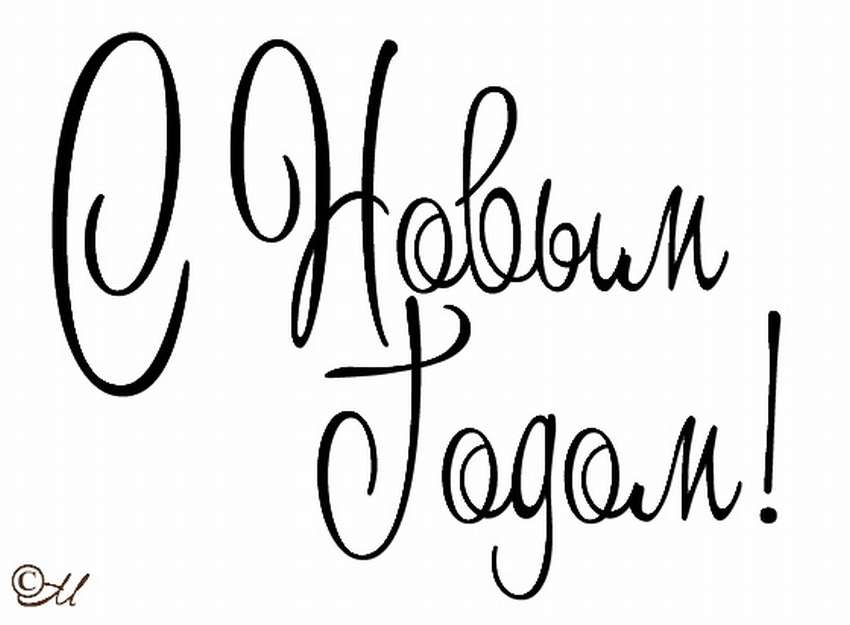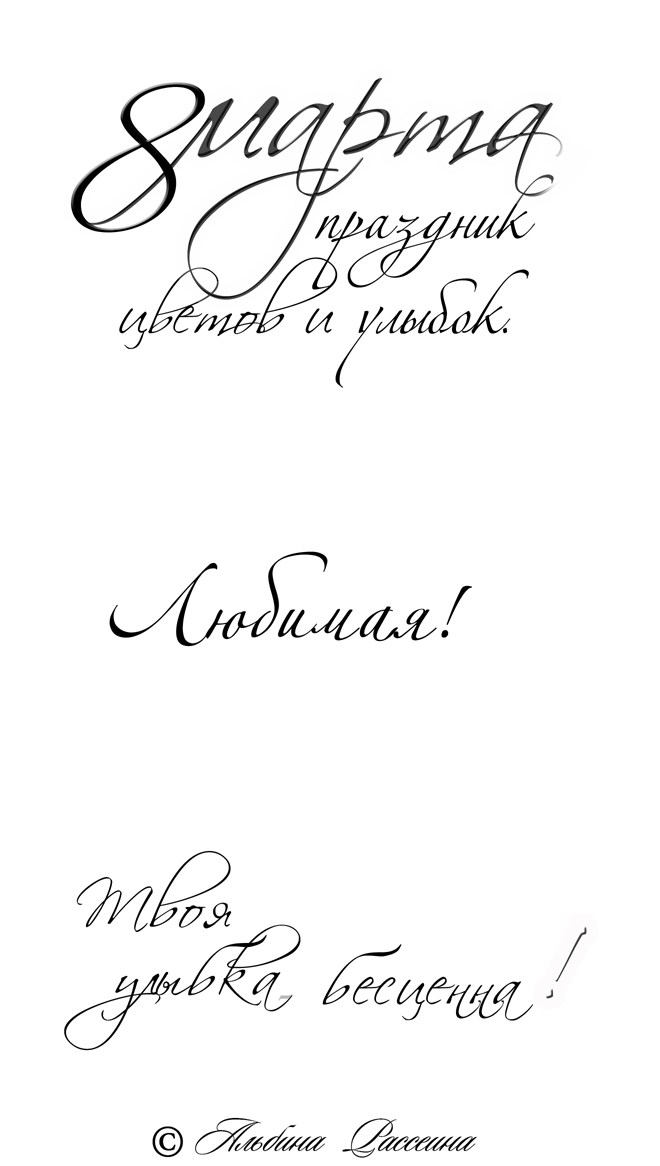
…Братушка делал корпоративную открытку ко Дню Победы.Серьезному строительному холдингу хотелось поздравить своих пенсионеров — фронтовиков, а депутатствующему директору компании – фронтовиков своего избирательного участка. Но не просто поздравить, а с душой и в фирменном стиле.
Рекламное агентство взялось выполнить заказ. А что – рядовая работенка.
С оборотом открытки проблем не возникло – логотип компании и место для поздравительного текста.
С лицом оказалось сложнее.
Поставить классического поднимающегося в атаку политрука? Избито.
Флаг над рейхстагом? Во всех газетах будет на первой полосе.
Сфотографировать местный Вечный огонь? Официозно.
Использовать старые плакаты? Старые открытки? «Родина-мать» и «Алеша». Не то. Все – не то. Эпоха сменилась. Чувства сменились…
Подумав, Братушка велел дизайнеру найти фотографию — алые маки по зеленому лугу, и на этом фоне написать четыре слова: «С ДНЕМ ВЕЛИКОЙ ПОБЕДЫ!».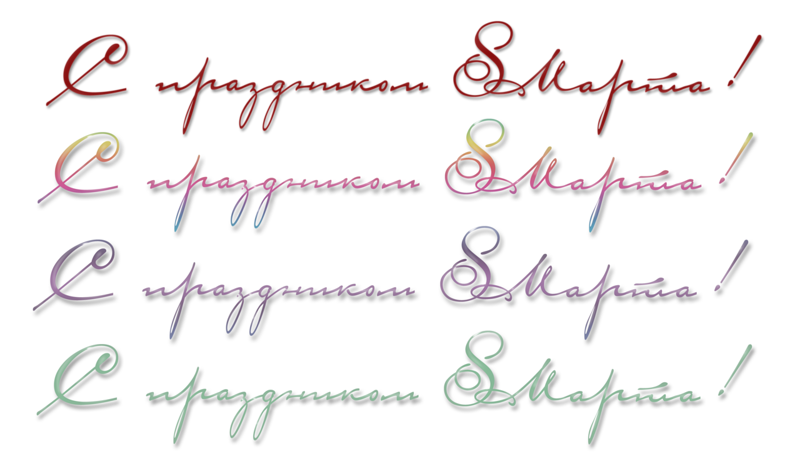
Снимок нашелся. Слоган поставили. Не играет!
Снимок правильный — щемящий до слез. А шрифт – бездушный. Чужой шрифт. Не из ТОЙ эпохи.
Сели выискивать среди компьютерных шрифтов такой, который бы визуально в пятидесятые отсылал. А не выходит. Получаются или революционные годы. Или излет восьмидесятых. Или вообще что-то эмоционально невнятное.
Сидят Братушка с дизайнером, перебирают по очереди шрифт за шрифтом. И после очередного клика видят картинку.
Новая зеленая жизнь, поднимающаяся на залитом маками, словно кровью, среднерусском поле. И под этим всем — написанное суровой готической (а может и вовсе – тевтонской) вязью — «С ДНЕМ ВЕЛИКОЙ ПОБЕДЫ!».
И тут Братушка словно в другую реальность провалился. Говорит: «Смотрю в монитор и вижу совсем другой парад на Красной площади. Другие знамена. Другие порядки. Слышу и дизайнер моя нервически хихикает и шепчет:
— Бли-ин, а если бы вот так вышло…»
…Запотыку со шрифтом решили по-старинке. Дизайнер взяла плакатное перо, и с трех попыток написала поздравление тушью.
Сосканировали, вставили. И да – стилистически наконец попали в конец сороковых — начало пятидесятых.
Заказчик был доволен. Фронтовики, говорят, даже плакали.
А Братушка тот случайный «тевтонский» вариант открытки уничтожил. Даже в качестве дизайнерской шутки никому показать не решился. Даже мне. Только на словах и поведал, что такое «страшно смешно» в историческом контексте.
Как приятно получать поздравления! Как приятно поздравлять!
Поздравительная открытка ручной работы – один из самых простых и в то же время изящных способов сделать приятно любимому, уважаемому, дорогому человеку.
В старину открытки появились как открытый вид письма — карточки с открытым текстом. После их стали украшать различными изображениями. Первая иллюстрированная открытка была напечатана во Франции.
Сейчас открытка, сделанная специально для человека, для мероприятия (пригласительная открытка на свадьбу) стала очень популярной, и получить её в подарок — всегда приятно!
Я считаю, что лучшая открытка – это открытка ручной работы, сделанная индивидуально для конкретного человека, учитывая его чувства, характер и интересы, потому, что самый дорогой подарок – это внимание и уважение.
В этом случае – авторская рукописная открытка – подходит более всего. Нарисованная профессиональным художником иллюстрация, с текстом, написанным от руки каллиграфическим почерком (шрифтом) придаёт простому подарку безупречную элегантность и изысканность. Такой подарок без сомнения дарить и получать очень приятно!
Именно каллиграфический шрифт передаст всю восторженность события, всю радость приближающегося праздника. Самим выбором шрифта, написанием букв уже можно угадать характер самого человека. Уже буквами — раскрыть образ нежной девушки, чопорной дамы, веселого юноши.
Красиво сочетать каллиграфические буквы с изображением, выстроить композицию меня учила моя лучшая преподавательница — Елена Анатольевна Дербилова. Эта потрясающая женщина вместила в себя и музыку (играла на скрипке), и танец (балет), и изобразительное искусство. Но по её мнению — рукописный шрифт вбирает все эти три понятия — он создаёт новую музыку, буквы — застывают танце…
Каждый раз, когда меня просят сделать открытку — я подхожу ответственно.
Данные примеры двух открыток — адресованы девушке. Поэтому они нежны и поэтичны, как сама получательница, а рукописным шрифтом я хотела передать её непоседливый характер.
По-моему – получилось.
20 лучших контурных шрифтов cкачать бесплатно Ⓐ Shriftkrasivo.ru
В итоге мы получаем текст, который выглядит волнистым.
Перейдите в Объект> Разобрать оформление. Это превратит наш текст в точки и линии, с которыми будет легче работать в следующих шагах.
Шаг 4. Измените цвета обводки и заливки
Мне нравится идея сильного контраста красных и черных теней, как на открытке Massachusetts , поэтому давайте перенесем эту концепцию в наш дизайн.Все, что нам нужно сделать, это изменить Обводку текста на красный (# D22323) и Заливку на белый (#FFFFFF). Мы завершим этот внешний вид на следующих этапах.
Шаг 5: Сделайте текст 3D